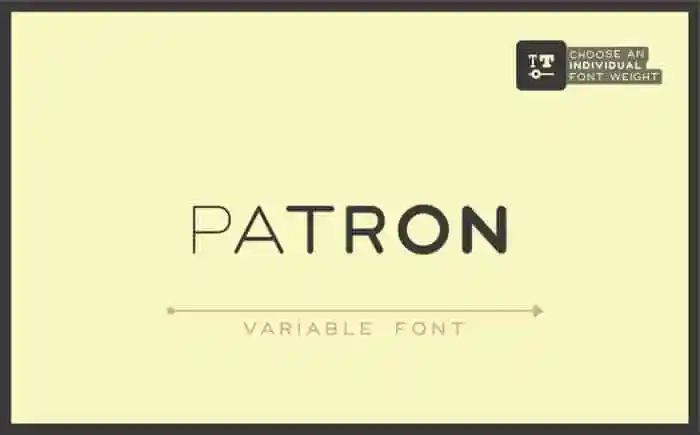
Patron Sans Serif Font – Download Grátis
A Fonte ‘Patron Sans Serif’ é uma escolha perfeita para designers que buscam estilos modernos e alegres sem perder a seriedade necessária para um design profissional. Esta tipografia sans serif foi criada com delicadeza, dando importância à aparência moderna dos caracteres ao adicionar bordas redondas, tornando-a ideal para logo, identidade visual, cartões de convite ou qualquer outra forma de comunicação gráfica. Ideal tanto para ambientes mais formais quanto para designs mais descomplicados e joviais, a fonte ‘Patron Sans Serif’ está equipada para dar um toque único aos seus projetos. Para aqueles que buscam uma paixão industrial, o designer oferece letras stencil em maiúsculas – uma excelente maneira de tornar os elementos do seu design ainda mais notáveis e memoráveis. Perfeito tanto para designers profissionais quanto para iniciantes, a ‘Patron Sans Serif’ é uma ótima opção para adicionar um toque único aos seus projetos. Sua simplicidade e elegância combinam com diversos estilos de marketing, tornando-a uma fonte versátil que não decepciona.